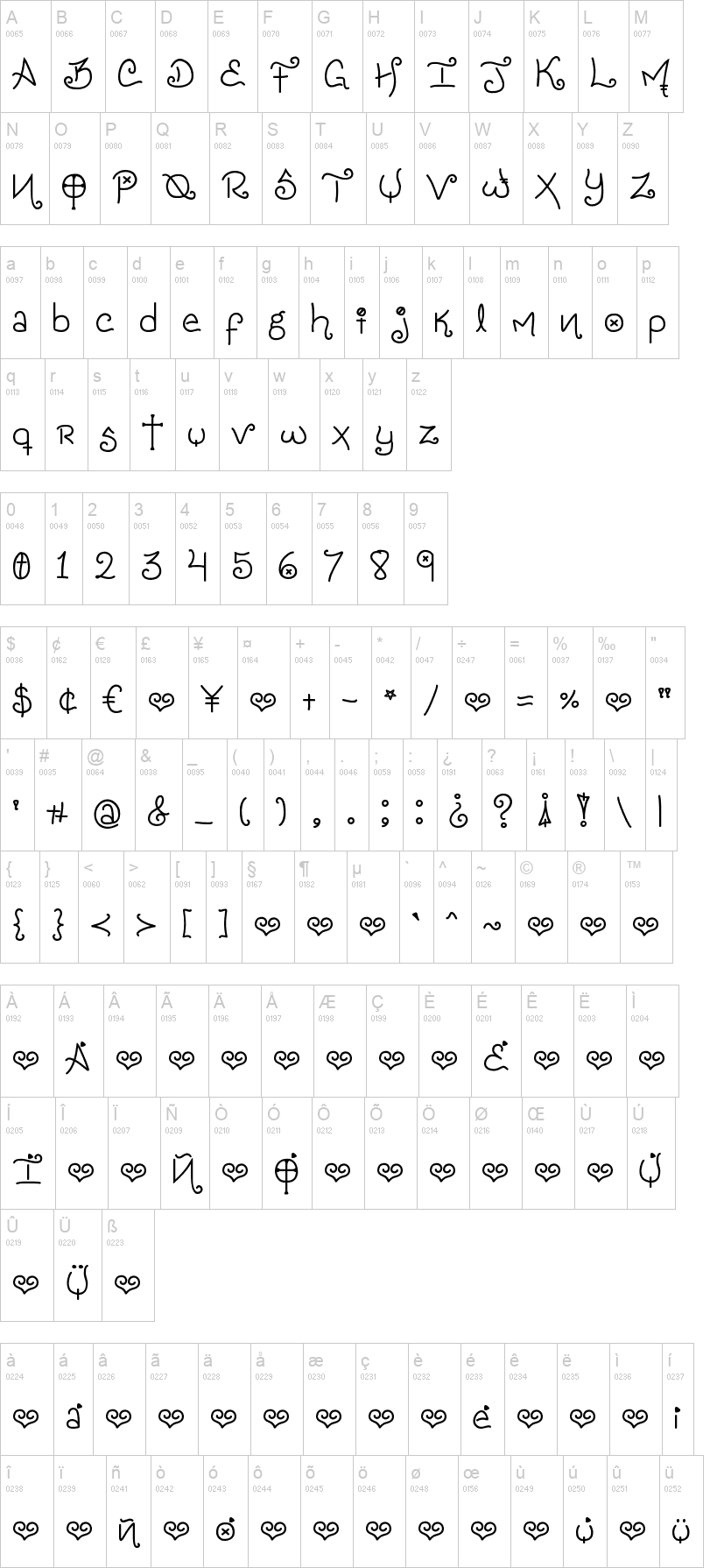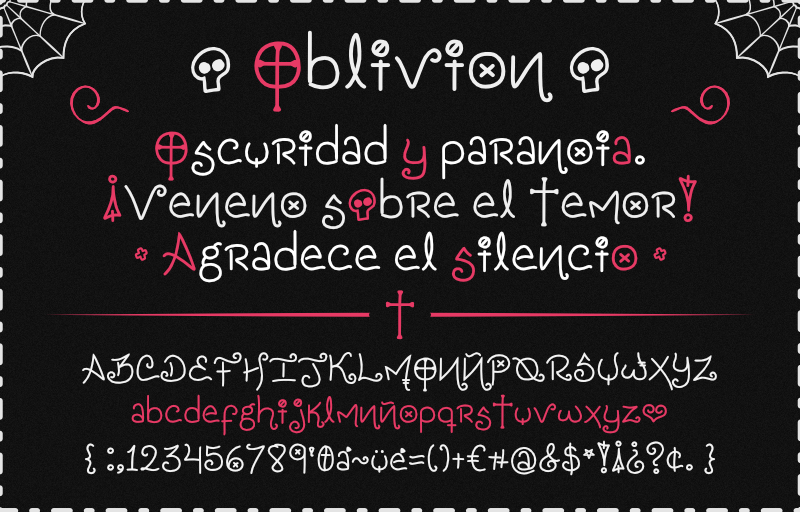
Note of the authorEsta font se basa en mi tipo de letra al escribir títulos. Con este signo "☺" puedes sustituir la -o- minúscula con una calavera.
This font is based on my typeface when I write titles. With this sign "☺" you can replace the lowercase -o- with a skull.